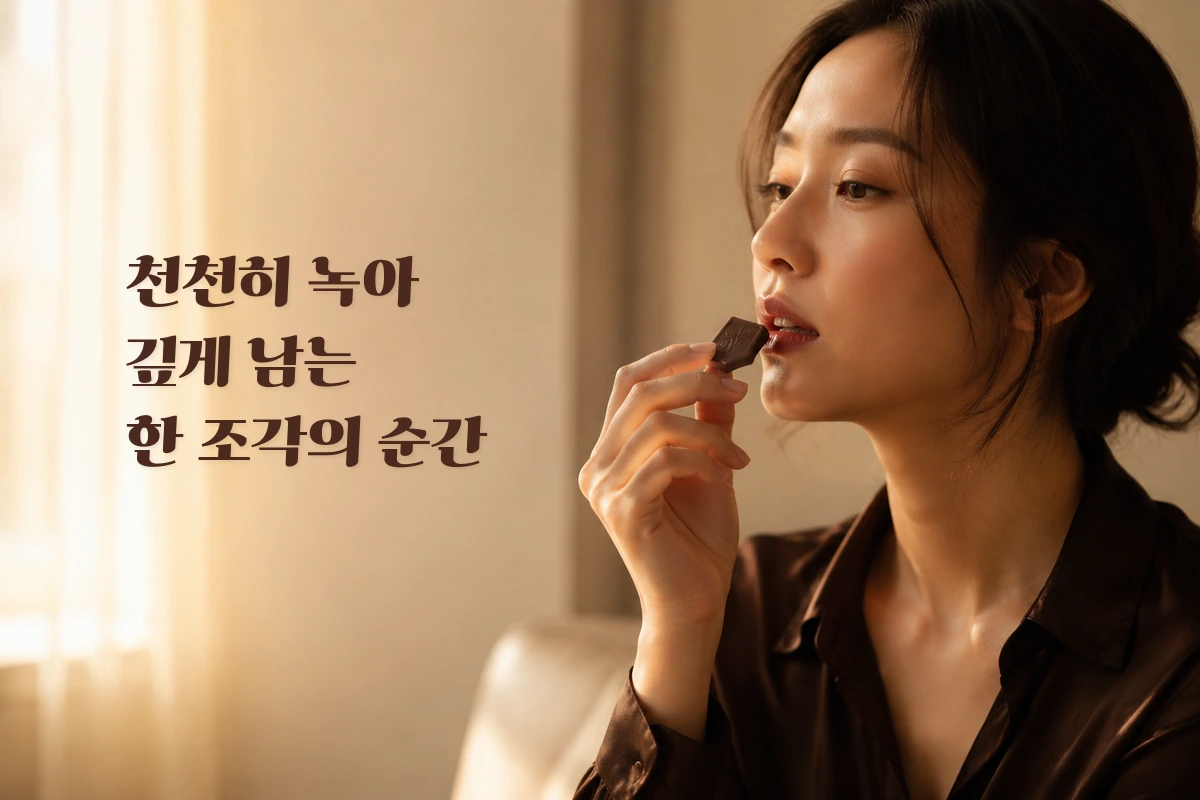
가나초콜릿 — 롯데웰푸드에서 배포하는 무료 폰트입니다. 부드러운 곡선과 단정한 글자 구조로 가나초콜릿의 고급스러운 이미지를 담은 서체
롯데가 1975년부터 만들어 온 가나초콜릿을 서체로 옮겨 2020년 2월, 밸런타인데이를 앞두고 공개한 글꼴입니다. 제작사는 가나초콜릿이 줄 수 있는 분위기와 풍미를 반영해 만들었다고 밝혔습니다.
조형에서 눈에 띄는 것은 기울기입니다. 보도자료에 따르면 약 3도의 미세한 기울기를 주고 곡선의 미를 살려 시각적으로 편안함과 부드러움이 느껴지도록 했습니다. 초콜릿을 부러뜨릴 때의 경쾌함과 입에서 녹는 부드러움을 함께 담으려 한 것입니다. 영문과 숫자는 기존 가나초콜릿 로고의 특징을 반영했고 한글과 어울리도록 같은 기울기를 적용했습니다.
굵기는 하나입니다. 제품 패키지에서 온 서체답게 짧고 굵게 읽히는 자리, 이를테면 제목이나 캐치프레이즈에 어울리고 긴 본문에는 맞지 않습니다.